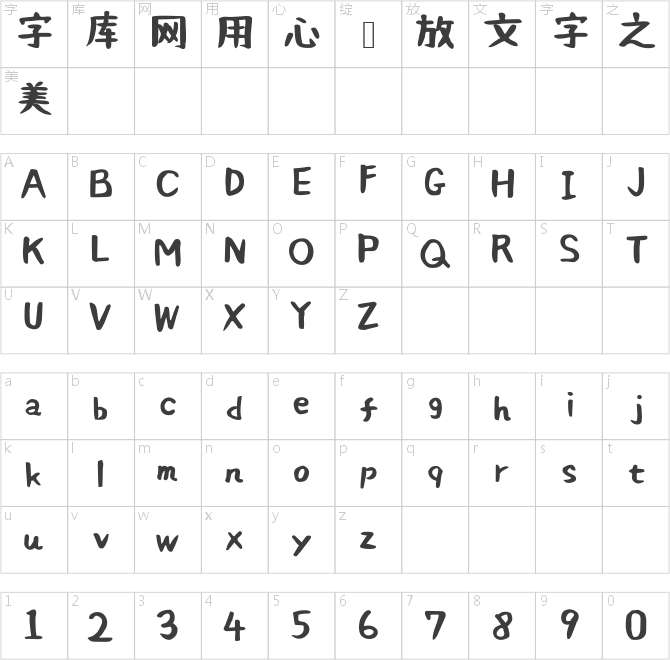
字体名称: 何某手写体
何某手写体是Max基于日本的おつとめフォント字体增补修改而成的一款随心所欲的手写体。与原作者的主要差异是调整部件写法、新增中文字、增加为5个字重、增加一些符号。经过Max的增补,何某手写体对简体的字体支持也挺不错的。
对现代人来说,毛笔字体不是可读性好的字体。但是手写文字和勘亭流等优秀的文字经常被用于促销用的传单和海报等。因此,何某手写体是根据毛笔文字的使用实际情况,重视“可视性高”为目标而制作的字体,大家不妨试一下哦。